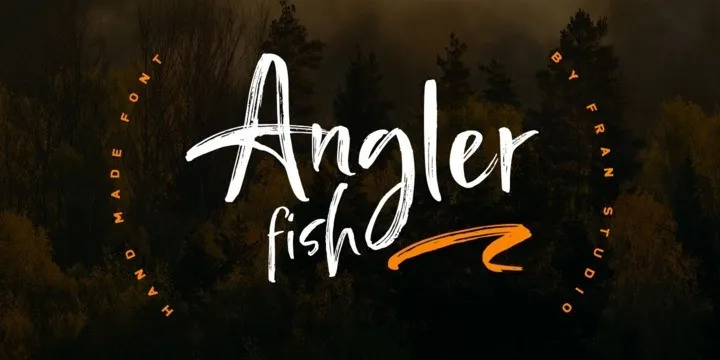
Descubra a encantadora Angler Fish Brush Font de Fran Studio, uma criação exótica e única no mundo dos tipos de tração manual. Este novo tipo de fonte é inspirado na escrita à mão com a ajuda de um pincel, resultando em uma fórmula script que se parece como uma escrita chinesa ondulada, moderna e lisa. Com seu design elegante e sofisticado, esta font oferece uma identidade visual única para qualquer projeto, seja ele branding, logotipos, embalagens de produtos, posters, convites ou até mesmo textos em blogs e sites pessoais que precisam de um toque de personalidade. Fran Studio trouxe à luz este tipo especializado e promete transformar seus projetos digitais no centro da atenção com a sua graça única e moderna.